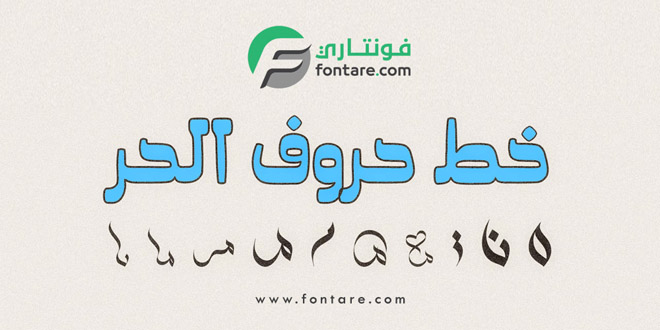
خط حروف الحر العربية .. خط زخارف حروف يوسف الحر الرائعة والتي يمكن استخدامها في أكثر من مجال وفي كافة التصاميم وأعمال الخطوط والشعارات، وطريقة الاستعمال بكتابة الأرقام الإنجليزية من (1) إلى (65) كما هو موضح في الدليل التالي.
طريقة الاستخدام : يكتب الخط بالأرقام الإنجليزية من رقم (1) إلى رقم (65)